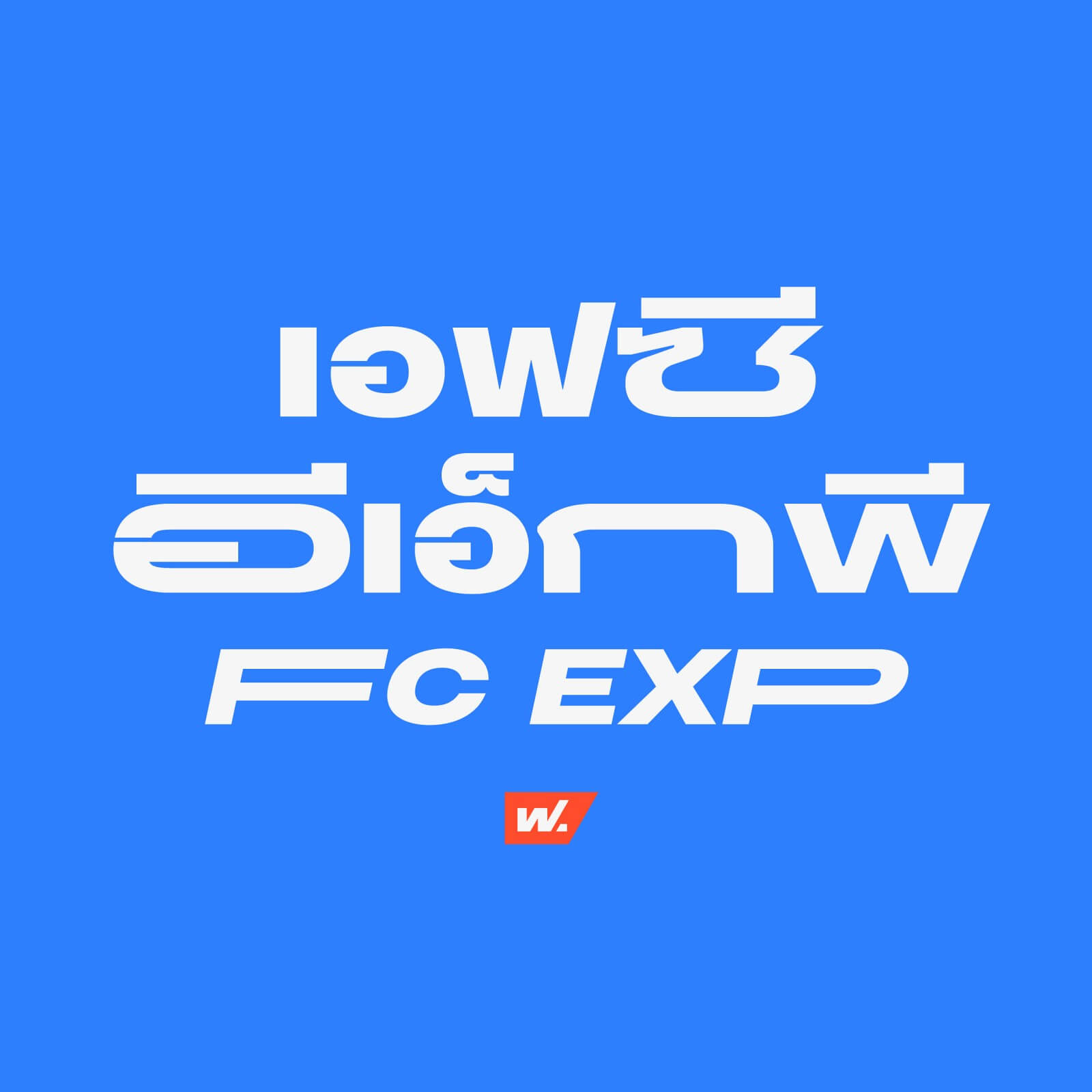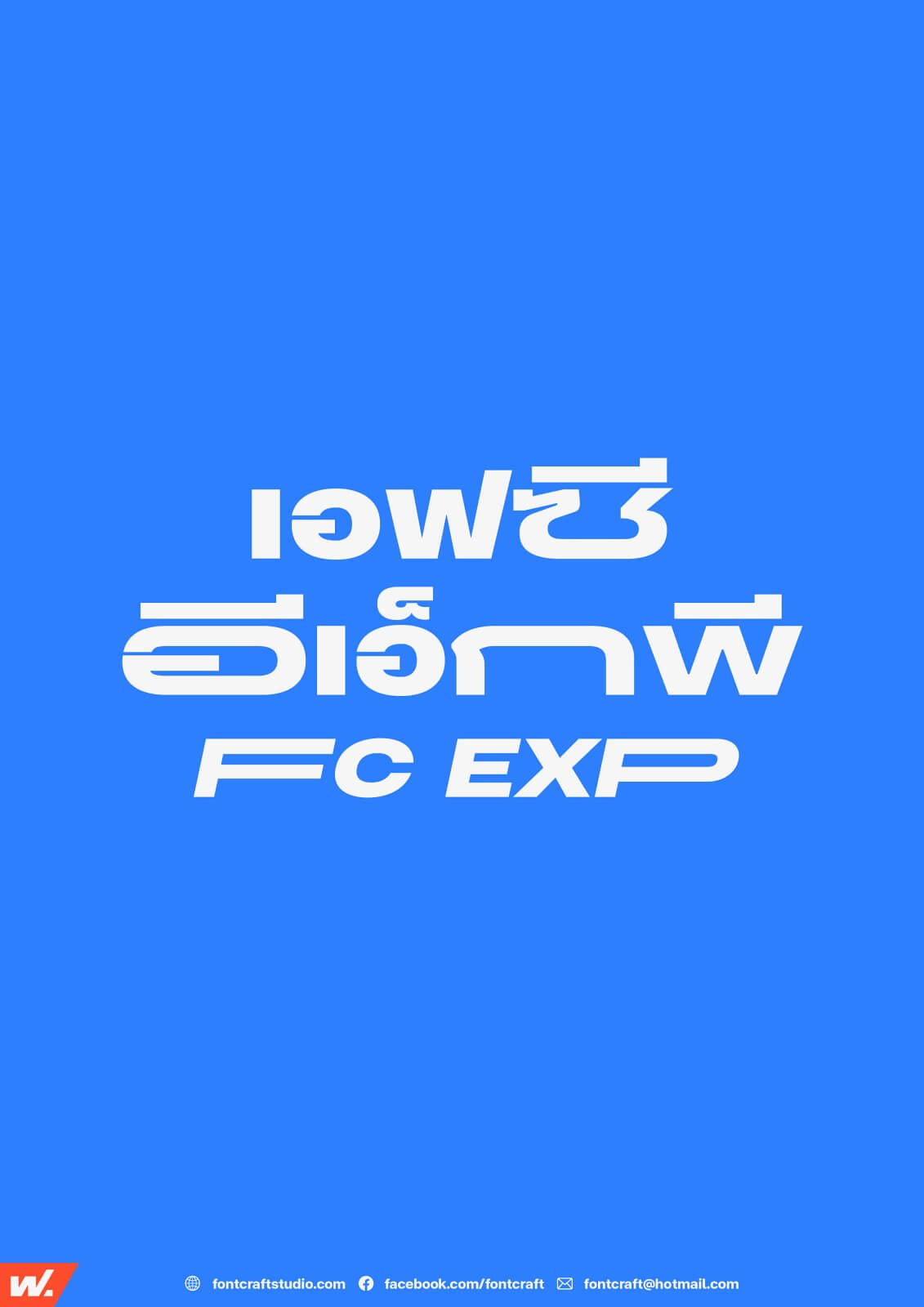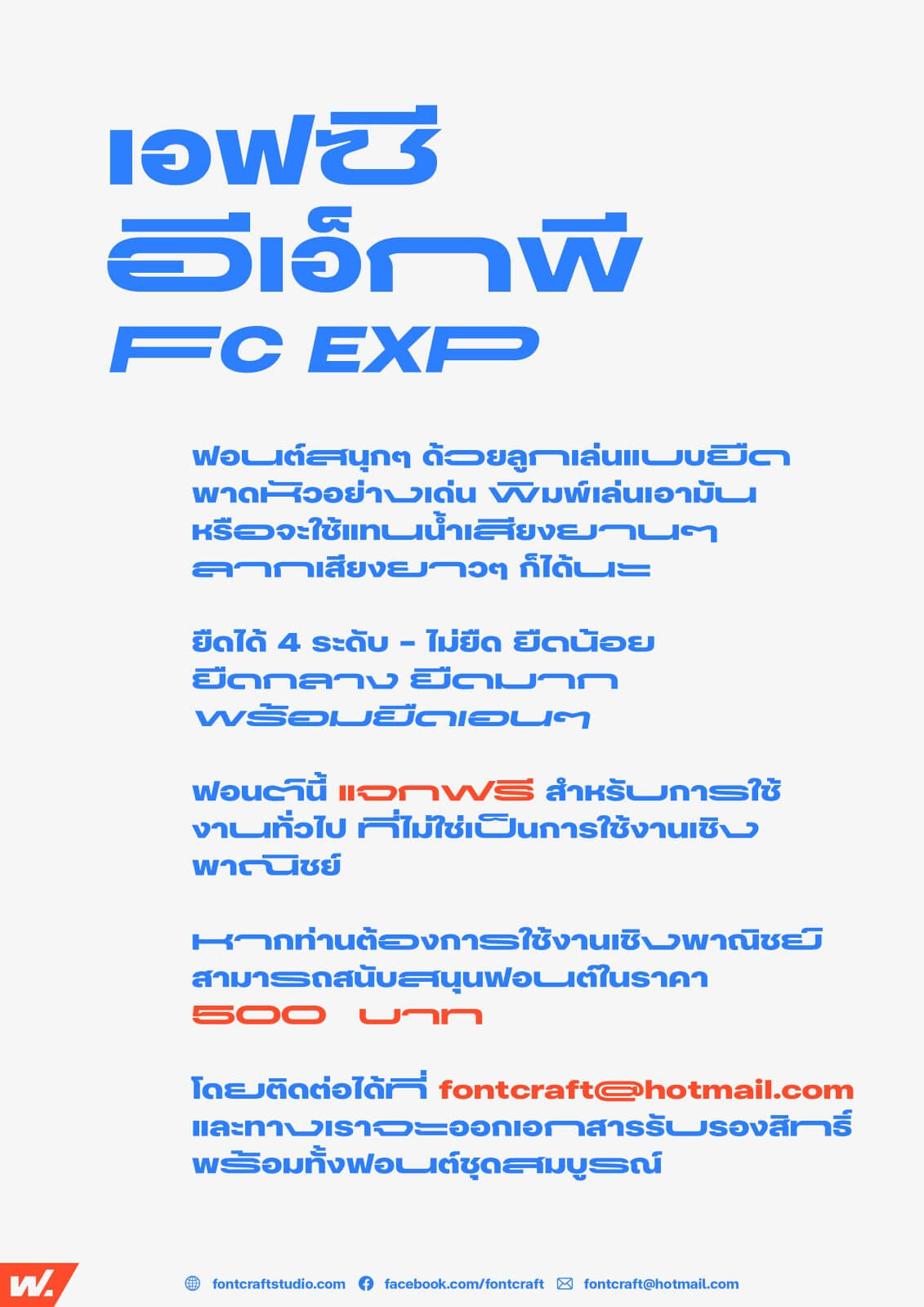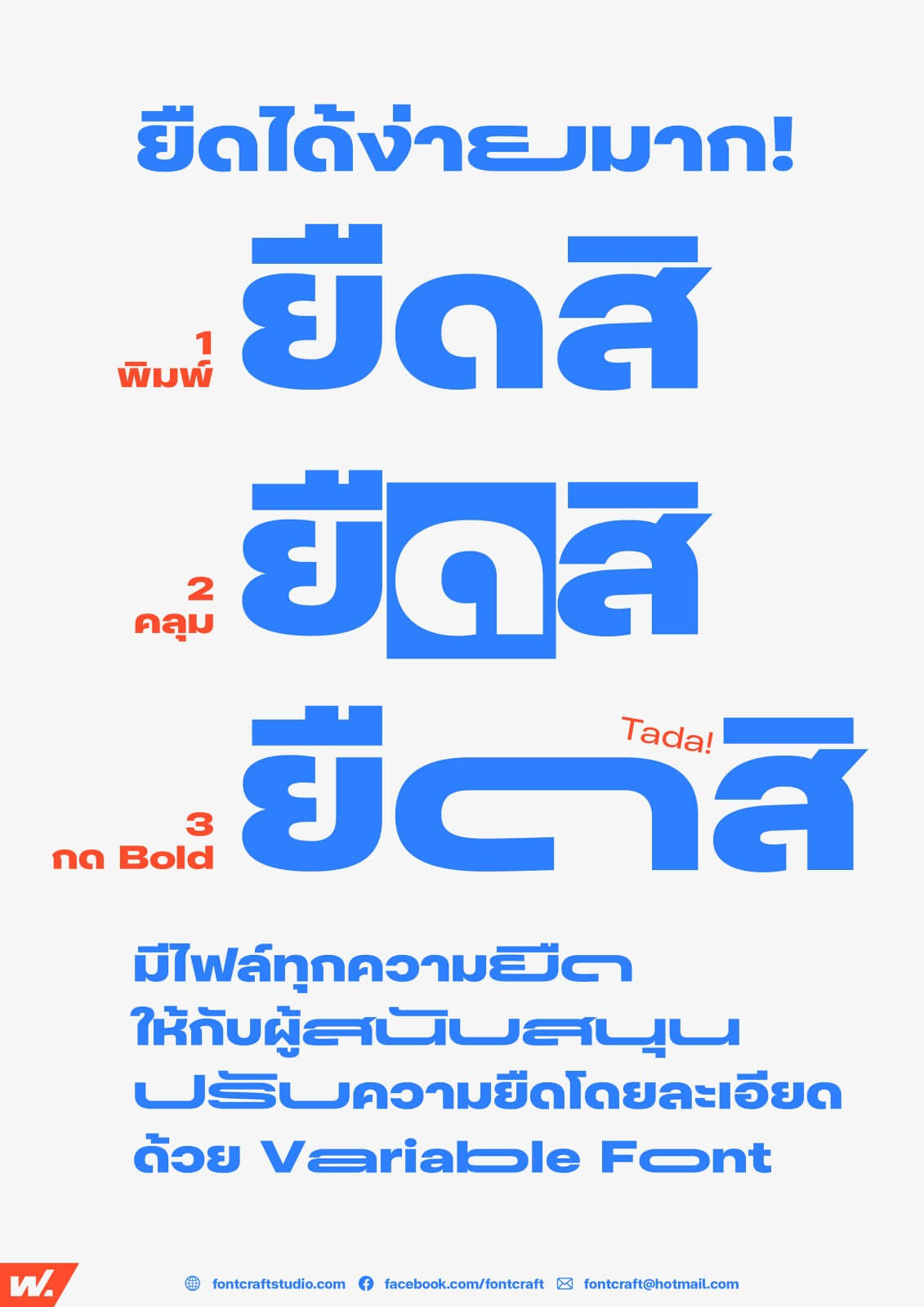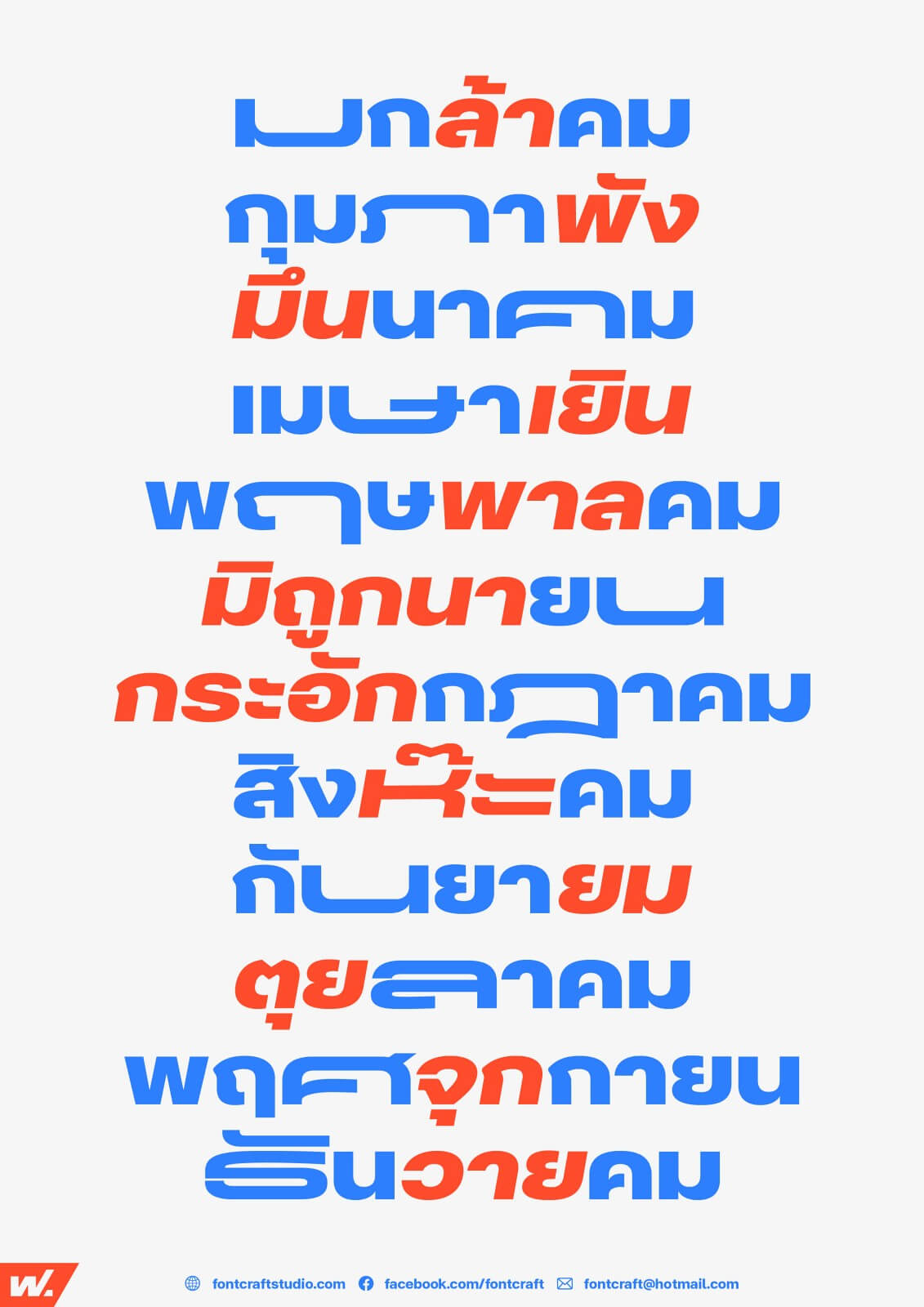
เอฟซี อีเอ็กซ์พี (FC EXP)
ฟอนต์สนุกๆ ด้วยลูกเล่นแบบยืด พาดหัวอย่างเด่น พิมพ์เล่นเอามัน หรือจะใช้แทนน้ำเสียงยานๆ ลากเสียงยาวๆ ก็ได้นะ
ชื่ออีเอ็กซ์พี (EXP) แปลได้หลายความหมาย
- Experiment ทดลองทำฟอนต์แบบแหวกแนว แล้วดูว่าฟอนต์จะพางานออกแบบไปได้ไกลขนาดไหน
- Expanded ฟอนต์นี้มีความกว้างแบบพิเศษ แถมทำให้ยืดได้ 4 ระดับ
- Experience ใช้ประสบการณ์จากฟอนต์ FC Vision ExtraExpanded มาเป็นพื้นฐานให้กับฟอนต์นี้ แถมใช้ร่วมกันกับ FC Vision Superfamily ได้อย่างลงตัว
วิธียืดฟอนต์ก็ง่ายมาก ลงฟอนต์ให้ครบ พิมพ์ข้อความ คลุมตัวอักษรที่ต้องการจะยืด แล้วกด Bold ได้เลย